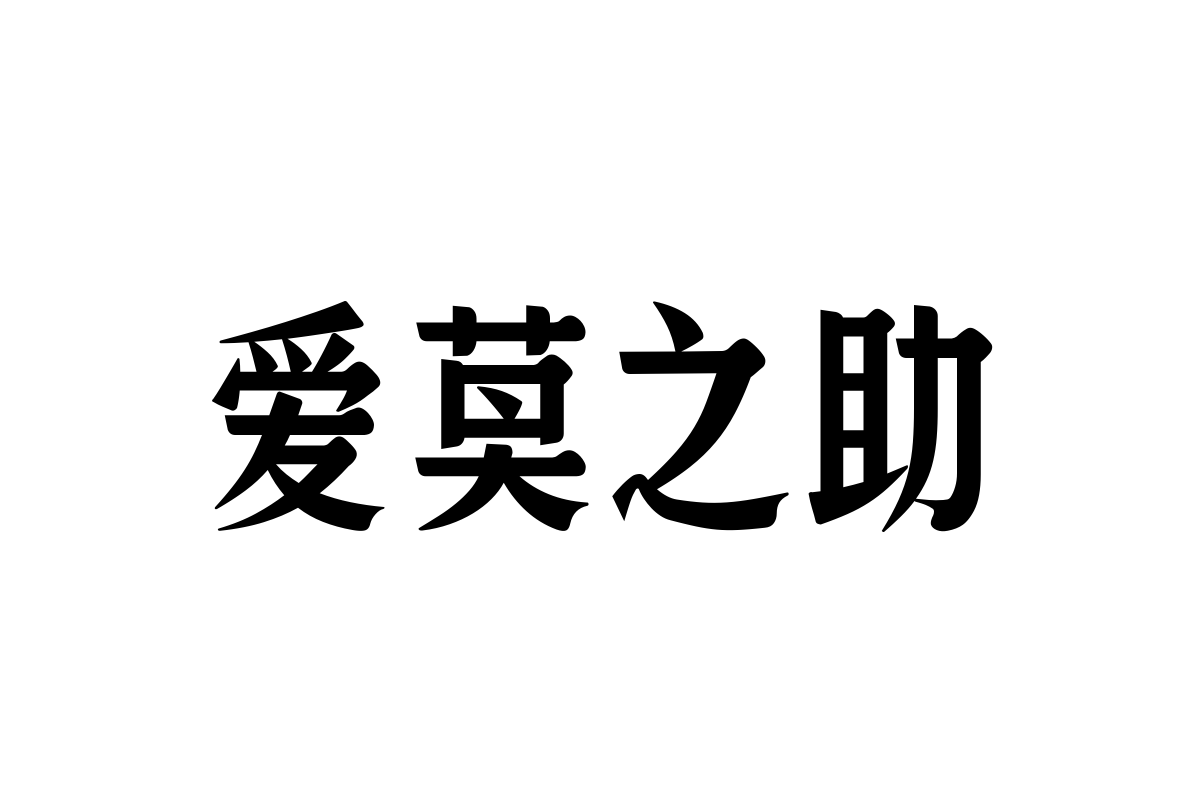
汉仪金陵美宋 W 字体是一款具有现代感和艺术气息的书法字体,适用于广告、设计、包装等领域。这款字体笔画流畅,结构紧凑,给人一种优雅而庄重的感觉。同时,它的线条粗细变化丰富,既有粗犷有力的笔触,也有细腻柔和的线条,适合表达不同的情感和意境。此外,这款字体还具有一定的辨识度和独特性,使得作品更加引人注目。